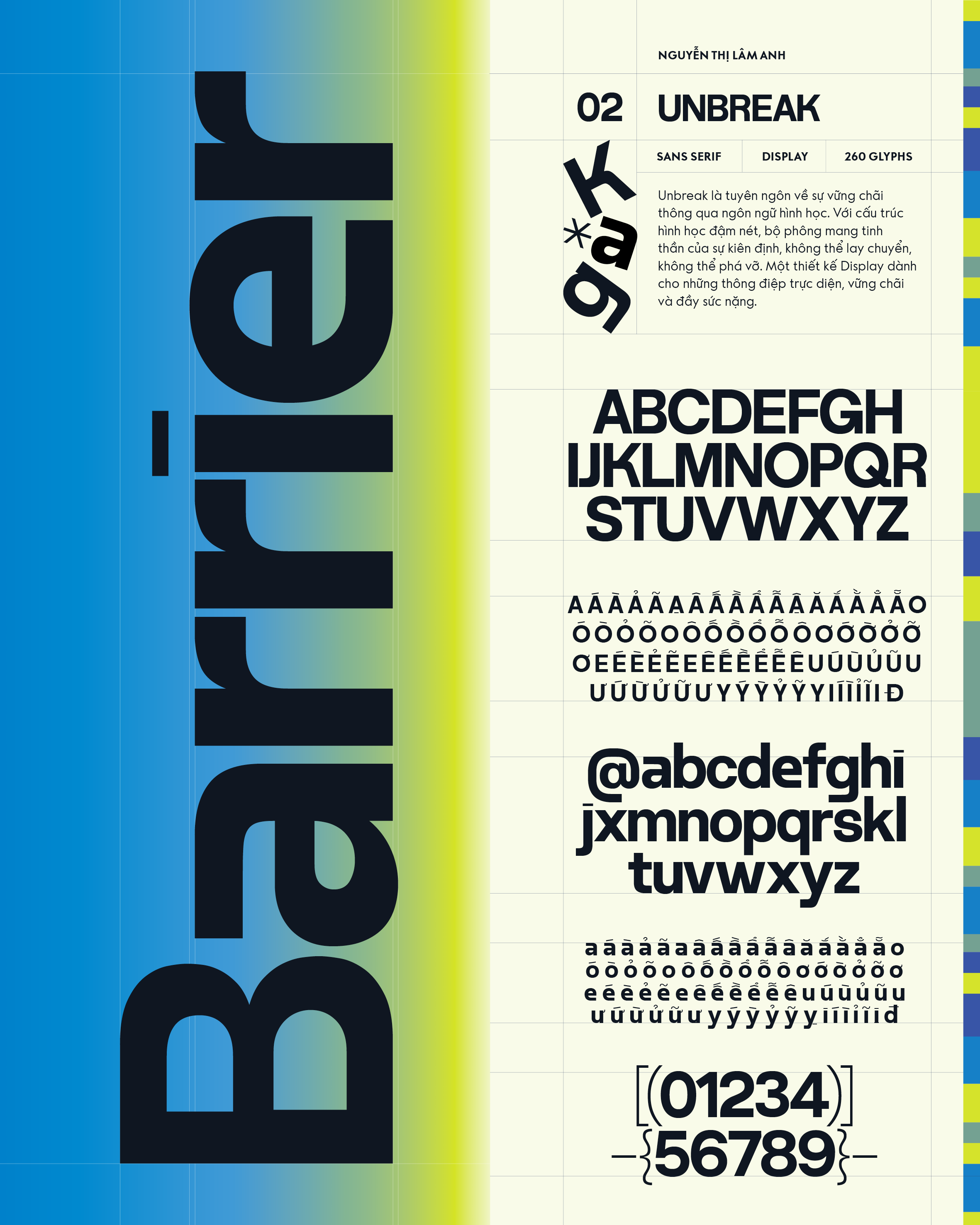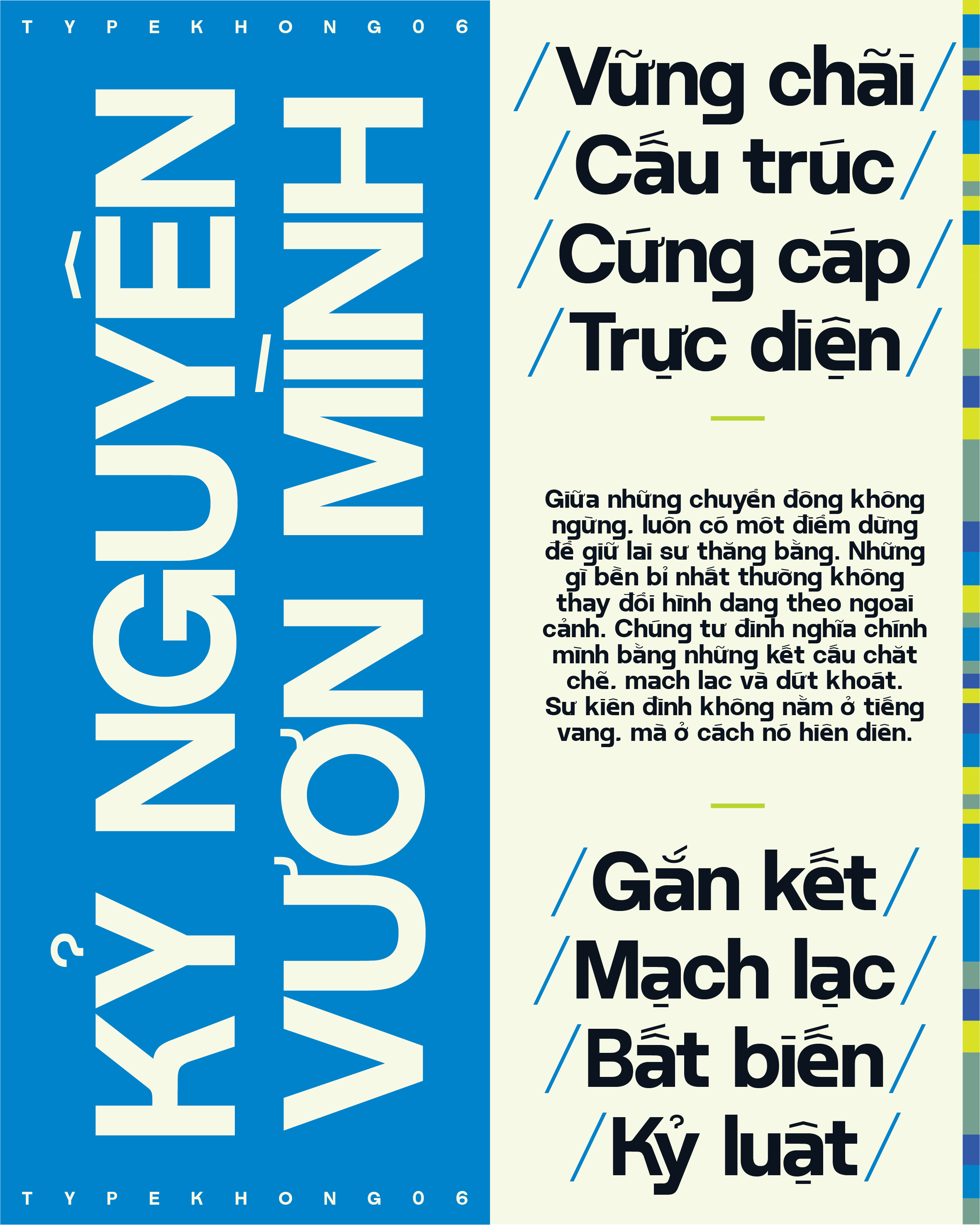
Unbreak
Về Unbreak: Unbreak là tuyên ngôn về sự vững chãi thông qua ngôn ngữ hình học. Với cấu trúc hình học đậm nét, bộ phông mang tinh thần của sự kiên định, không thể lay chuyển, không thể phá vỡ. Một thiết kế Display dành cho những thông điệp trực diện, vững chãi và đầy sức nặng.
Grotesk Sans-serif
Display
Nguyễn Thị Lâm Anh
Unbreak
Barriers
Unbreak
Line Delivery
Unbreak
Bất biến
Unbreak
Cấu trúc ổn định